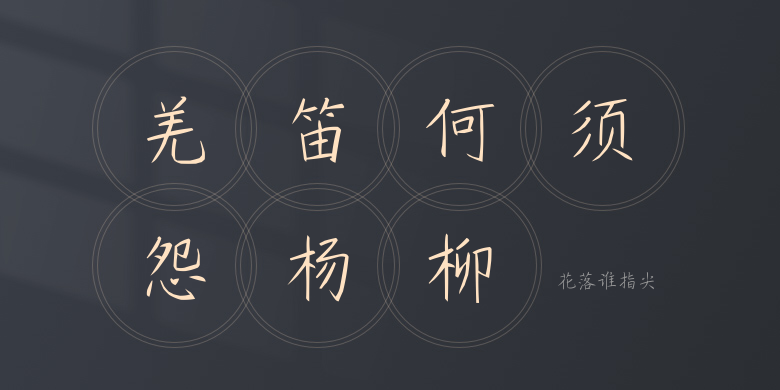
花落谁指尖
花落谁指尖,这款字体结构工整、笔画清晰,兼顾美观与易读性,适用于标题、正文、海报、包装、LOGO 等多种场景。字形优雅稳定,风格百搭耐看,适配日常排版与创意设计,让文字呈现更舒适、更具质感。花落谁指尖一笔一画,皆是细节,以均衡的比例、流畅的线条打造舒适视觉体验,字形端正大气,风格简约现代。无论是商业设计、品牌宣传还是日常排版,都能轻松驾驭,让文字更有格调与力量。花落谁指尖字体下载。